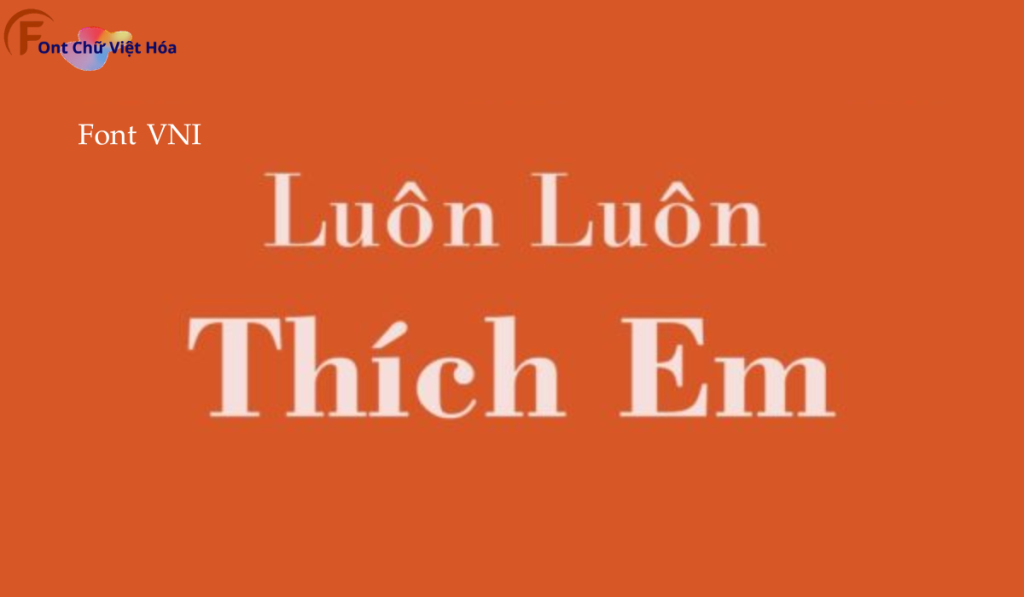
Font VNI Bodon Việt Hóa
Tác giả: VNI Bodon
Bộ Font: Font VNI
Phân loại: Cổ điển, Trang trọng
Kiểu chữ: Có chân
Độ dày: Regular, Bold, Italic
Font VNI Bodon Việt Hóa, thuộc bộ font VNI, mang phong cách cổ điển và sang trọng, phù hợp cho các dự án thiết kế như thiệp mời, bìa sách, và tài liệu văn phòng. Với các nét chữ có chân và độ dày đa dạng, Font VNI Bodon Việt Hóa không chỉ dễ đọc mà còn tạo cảm giác lịch lãm và chuyên nghiệp. Việc Việt hóa font giúp người dùng dễ dàng tích hợp vào các thiết kế tiếng Việt, mang lại sự tiện lợi và nâng cao tính thẩm mỹ.